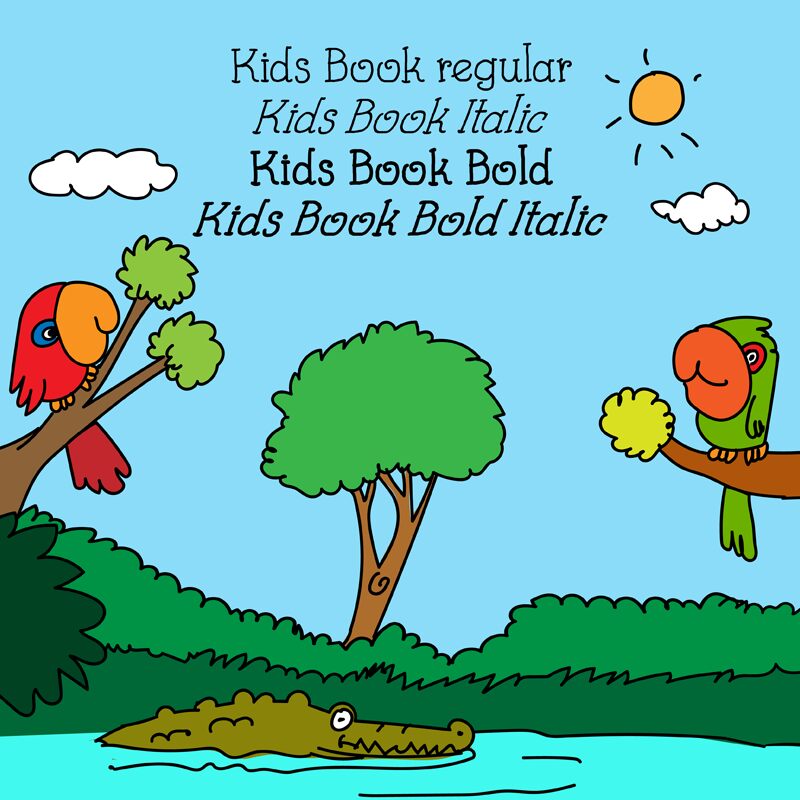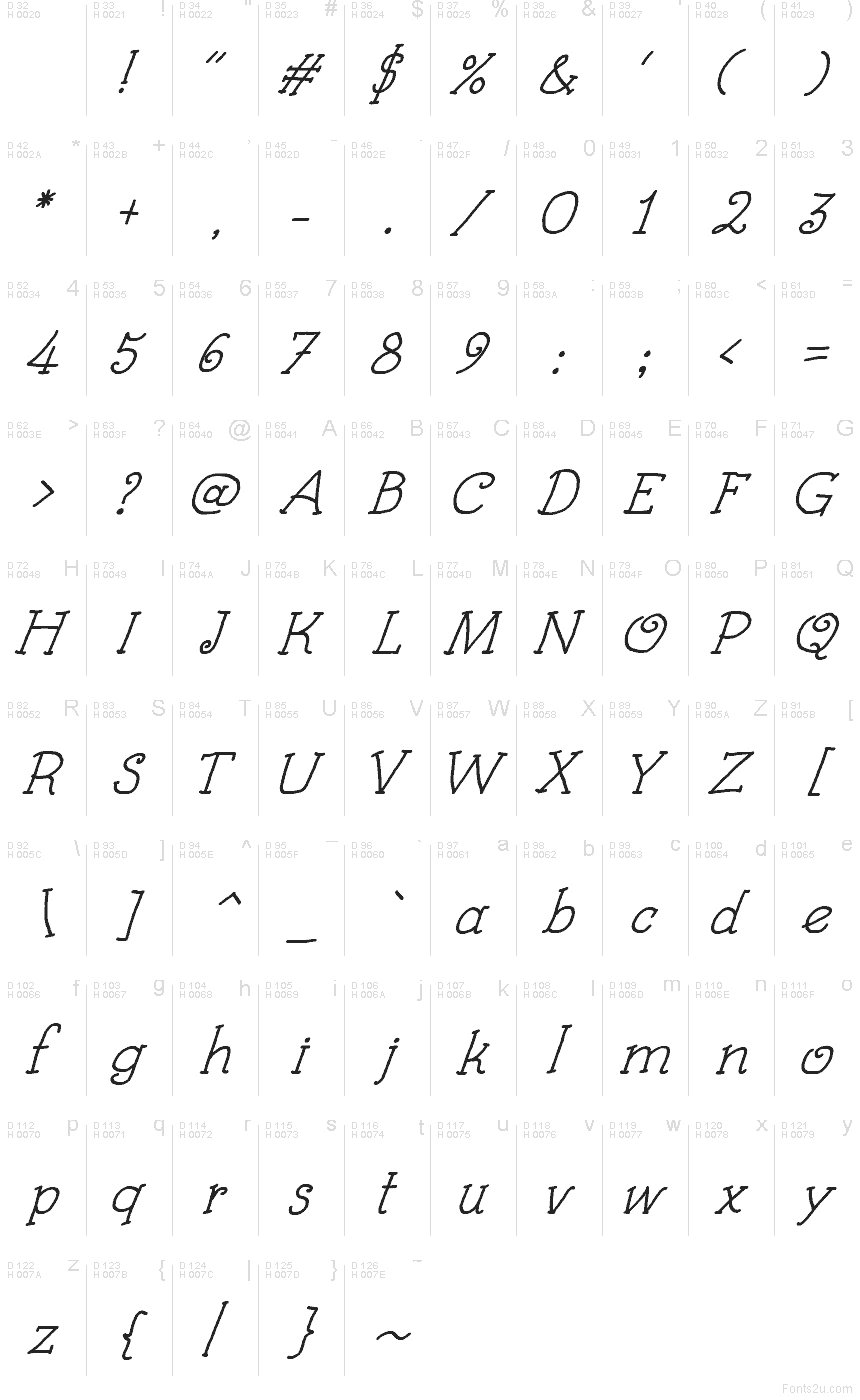
Kids Book Italic od Galdino Otten je bezplatné ručně psané písmo, kterému vdechuje život uvolněný rytmus knižních příběhů a vysoké, lehce kolébající se tahy. Písmena v sobě spojují rychlý pohyb štětce s kadeřavými detaily, což jim dodává hravost dětských čítanek, spíše než jen dojem obyčejného písma.
Tento živý rytmus skvěle vynikne na školních plakátech, obálkách knih pro začínající čtenáře, narozeninových pozvánkách, pracovních listech i hravých obalech. Nejvíce těží z krátkých nadpisů a jmen, kde dlouhé křivky a veselý sklon dodávají každému řádku živý, přirozený pocit, který se hodí pro dětské návrhy, aniž by působil jako laciný efekt.